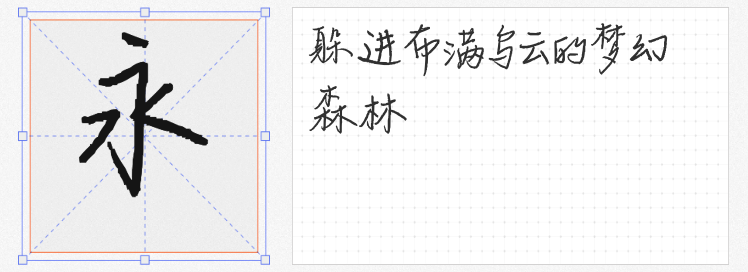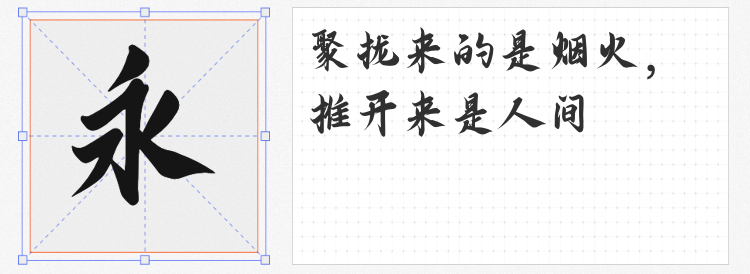
在七夕佳节来临之际,设计师们总在寻找那些既能传递节日氛围,又能彰显独特创意的字体。今天,就为大家推荐四款免费商用且极具特色的字体,让你的七夕设计作品脱颖而出。
1. 重庆山城棒棒体
这款由云峰字库推出的免费字体,承载着对重庆山城棒棒军这一即将消失职业的深切怀念。其独特的字形设计,仿佛能让人看到棒棒军们肩扛重担、穿梭于山城巷弄间的坚韧身影。虽然它没有编码英文字母、阿拉伯数字和符号,但在七夕主题的中文设计中,它绝对能成为传递情感与记忆的独特载体。
2. 栗壳坚坚体
一款充满手写温度的字体,由作者逐字书写后精心扫描进电脑。每一笔一划都透露出书写者的真挚情感,让设计作品瞬间充满人情味。在七夕这样的浪漫节日里,用栗壳坚坚体书写情话或祝福,定能让接收者感受到满满的心意。
3. 淘宝买菜营销体
作为淘宝买菜与通义锦书联手打造的AI个性化字体,它融合了现代科技与艺术美感。独特的字形设计,既符合当下审美趋势,又能轻松吸引眼球。在七夕营销活动中使用这款字体,无疑能为品牌增添一抹亮色。
4. 也字工厂小石头体
这款字体以其Q弹可爱的字形和温暖亲切的感觉赢得了众多设计师的喜爱。笔画的自由书写与软笔的圆润特征相结合,使得字体既灵动活泼又不失亲和力。在七夕设计作品中运用小石头体,定能让你的创意更加生动有趣,吸引更多目光。
这四款免费商用字体各具特色,无论是传递情感、增添温度还是吸引眼球,它们都能成为你七夕设计中的得力助手。不妨尝试将它们融入你的作品中,让创意与浪漫并存!